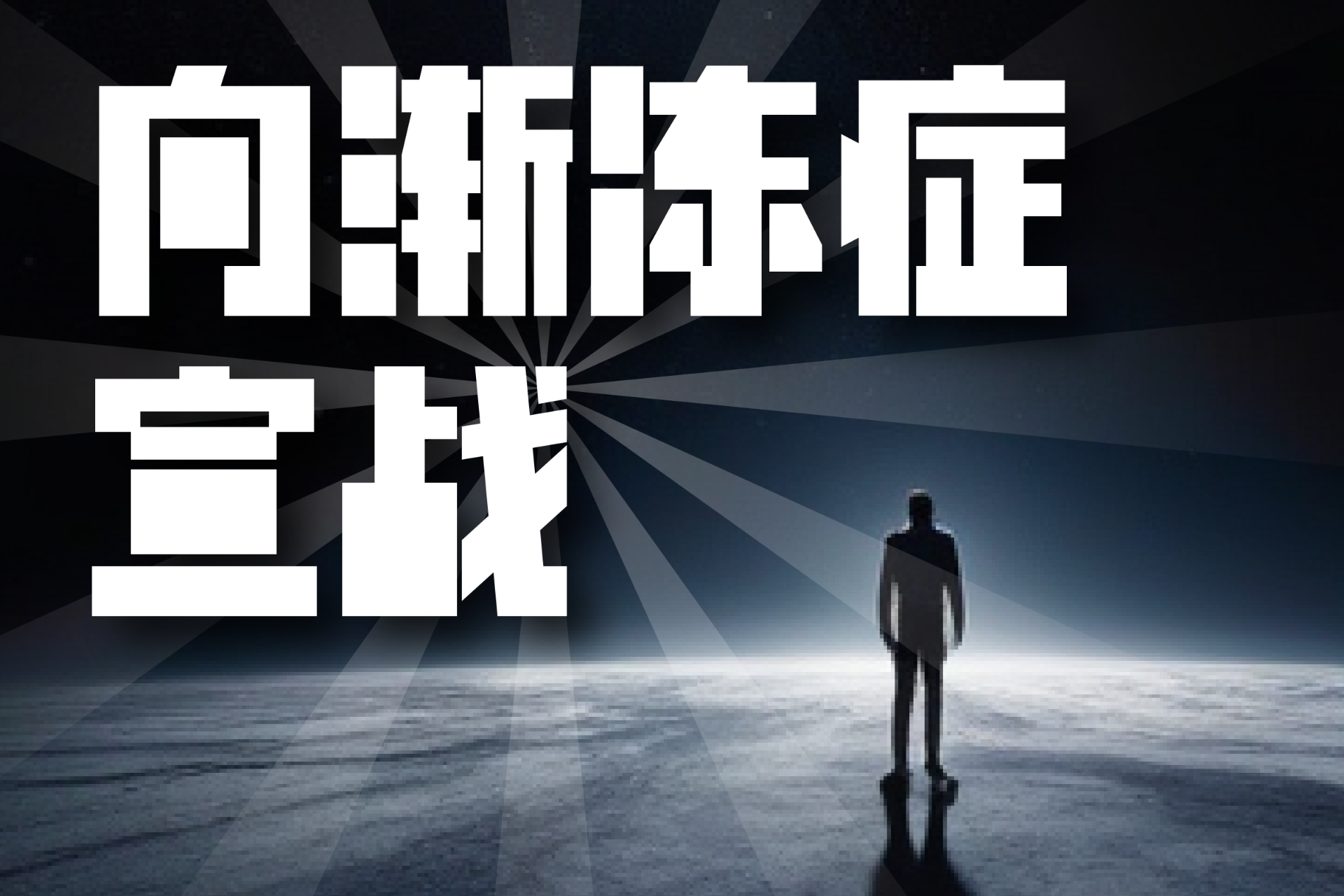
💫创意无限!四款广告设计必备字体推荐💫
在广告设计中,字体不仅是信息传递的载体,更是情感传递和艺术表达的媒介。以下四款字体,以其独特的设计风格和广泛的应用场景,成为广告设计师的得力助手。
“草在结它的种子,风在摇它的叶子。”这款字体仿佛捕捉了自然界的韵律,笔画摇摇晃晃,歪歪扭扭,充满了手写体的温暖与亲切。其失衡夸张的设计,不仅增添了视觉趣味性,更能引发观众的情感共鸣。适用于需要传递温馨、自然氛围的广告设计,如环保主题、生活类产品推广等。
二、喵字渐冻体
喵字渐冻体是一款具有深远意义的字体,其设计初衷是为了让大众更加直观地了解渐冻症患者的痛苦与挣扎。通过模拟渐冻症的病理特征,这款字体以独特的方式引起社会的广泛关注。在广告设计中,它不仅可以用于公益宣传,还能为品牌注入社会责任感,提升品牌形象。
三、励字美黑简
励字美黑简融合了黑体与宋体的优点,字体匀称、清秀美观,给人端正又正气的视觉效果。在广告设计中,它适用于需要传递正式、严谨信息的场景,如金融、法律、教育等领域的广告宣传。其清晰易读的特性,也能确保信息的高效传递。
四、字圈也字多肉体
字圈也字多肉体字型圆润饱满,Q弹可爱,给人和善可亲的感觉。其“破方为圆”的设计手法,将转折写成流动感的圆弧形状,形成了一个个封闭的圆环,妙趣横生。在广告设计中,它特别适用于儿童产品、娱乐产业等需要传递快乐、童真氛围的场景。
这四款字体各具特色,无论是传递温暖、表达关怀、展现正气还是营造童趣,都能为广告设计增添独特的魅力。选择适合的字体,不仅能让广告更加吸引眼球,还能更深入地触达目标受众的心灵。